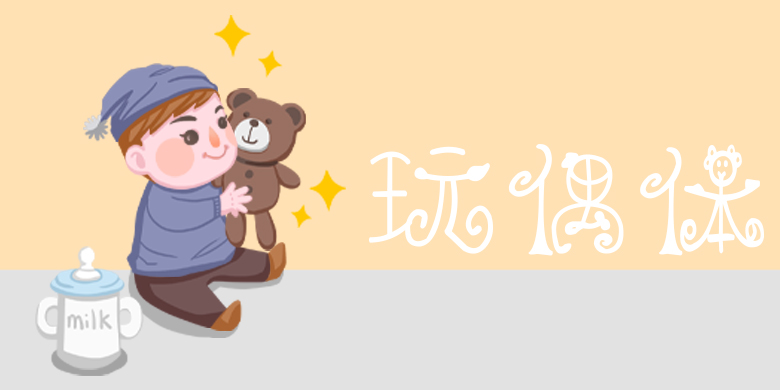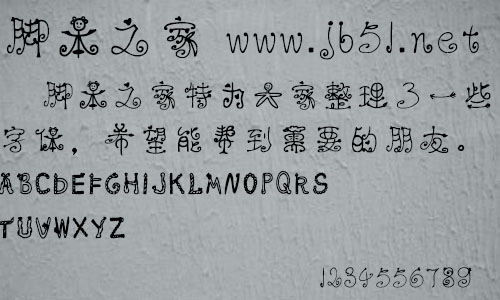
方正玩偶體由方正字庫李瀟設(shè)計(jì)師出品的藝術(shù)字體,字體大膽地對一些元素進(jìn)行提練,進(jìn)而直接用到部件筆畫中,適合應(yīng)用于藝術(shù)設(shè)計(jì)、平面宣傳設(shè)計(jì)、網(wǎng)頁設(shè)計(jì),書法等領(lǐng)域。
這款字體大膽地對一些元素進(jìn)行提練,進(jìn)而直接用到部件筆畫中,因而每個(gè)字看起來都像一個(gè)事物。是值得細(xì)品的字體,極具趣味性。適用于少兒類書刊,及現(xiàn)代詩歌、短文的排版以及文化、商業(yè)類品牌的廣告語設(shè)計(jì)。。